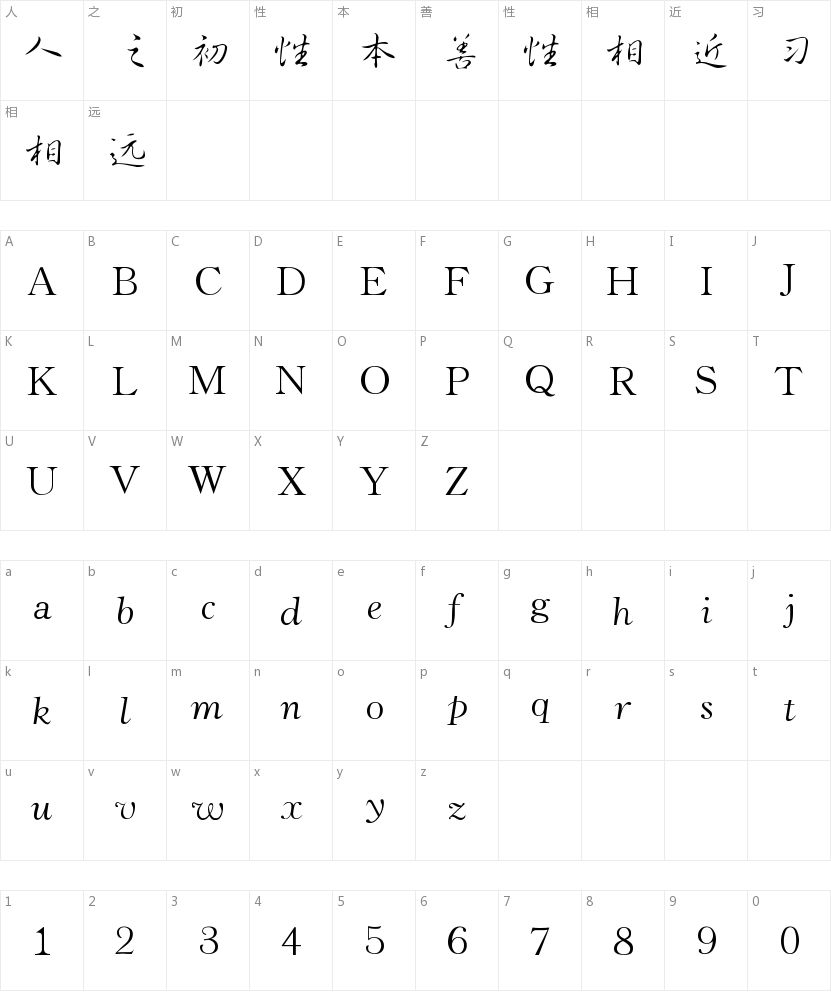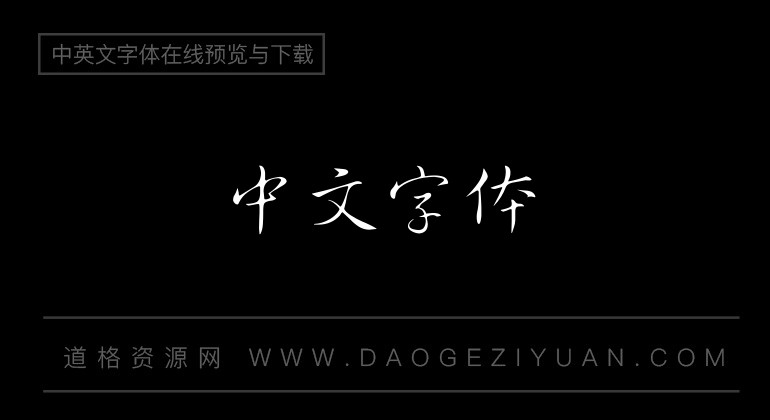
锐字云字库行草体GBK
锐字云字库行草体GBK字体是一款毛笔字体,它具有清新、古朴、稳重的风格,深受传统文化爱好者的喜爱。它采用行草体的设计风格,每个字符都充满了古朴的气息,让人仿佛置身于古老的文化氛围中。此外,它还具有极好的可读性和可视性,使用它可以有效提高文字的表达效果。
锐字云字库行草体GBK是一款非常不错的手写艺术字体,具有很好的视觉感,适合于文化类的宣传设计、商业类品牌的广告和产品包装设计以及个性化文字排版等较多场景。